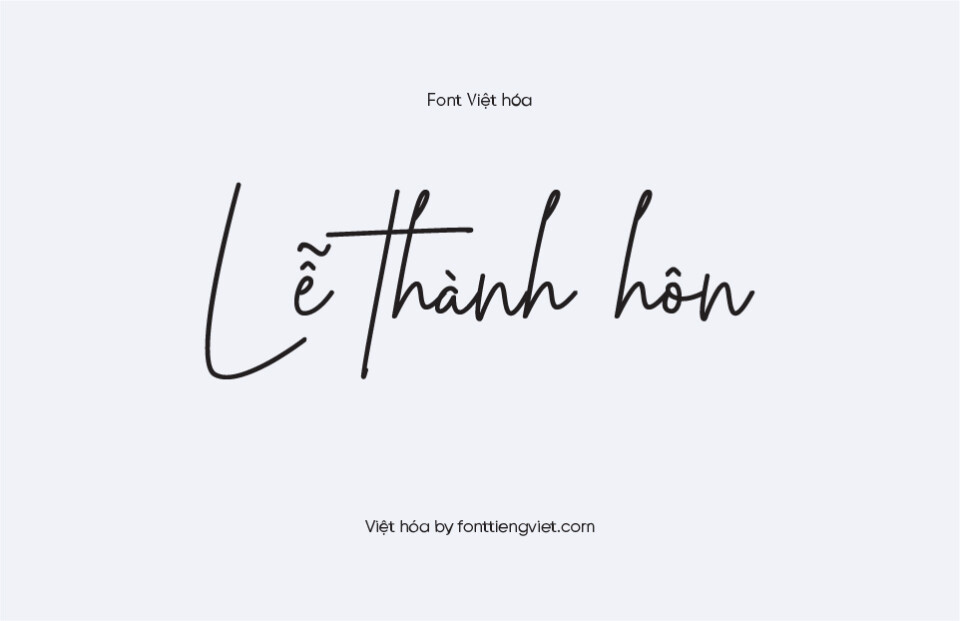
Font Việt hóa 1FTV VIP South Australia
Giới thiệu về Font Việt hóa 1FTV VIP South Australia
Trong thế giới thiết kế đồ họa hiện đại, việc tìm kiếm một bộ font vừa mang tính thẩm mỹ cao vừa hỗ trợ đầy đủ tiếng Việt là điều vô cùng quan trọng. Font Việt hóa 1FTV VIP South Australia nổi lên như một lựa chọn hàng đầu cho các nhà sáng tạo nội dung và học sinh, sinh viên. Đây là một bộ Font Miễn Phí được tinh chỉnh kỹ lưỡng, giúp loại bỏ hoàn toàn các lỗi hiển thị dấu câu thường gặp trong các bộ phông chữ ngoại nhập. Với phong cách thanh lịch và hiện đại, bộ chữ này mang lại cảm giác phóng khoáng nhưng vẫn giữ được sự chuyên nghiệp cần thiết cho mọi sản phẩm thiết kế từ đơn giản đến phức tạp.
Đặc điểm nổi bật của Font Việt hóa 1FTV VIP South Australia
Thiết kế tinh tế và tính ứng dụng cao
Bộ Font Việt hóa 1FTV VIP South Australia sở hữu những đường nét mảnh mai nhưng chắc chắn, tạo nên sự cân đối hoàn hảo trên mặt giấy cũng như màn hình kỹ thuật số. Cấu trúc của các ký tự được thiết kế dựa trên cảm hứng từ vẻ đẹp tự nhiên của vùng Nam Úc, mang đến một hơi thở mới lạ cho cộng đồng thiết kế tại Việt Nam. Độ dày của các nét chữ được tính toán tỉ mỉ để đảm bảo tính dễ đọc ngay cả khi sử dụng ở kích thước nhỏ. Điều này giúp bộ font trở nên cực kỳ linh hoạt, phù hợp cho cả tiêu đề lẫn nội dung văn bản dài mà không gây mỏi mắt cho người xem.
Tối ưu hóa tiếng Việt hoàn chỉnh
Điểm mạnh nhất khiến Font Việt hóa 1FTV VIP South Australia trở nên phổ biến chính là khả năng hiển thị tiếng Việt xuất sắc. Các dấu thanh như huyền, sắc, hỏi, ngã, nặng được đặt ở vị trí chuẩn xác, không bị đè lên ký tự chính hay bị lệch khoảng cách. Đối với các bạn học sinh đang thực hiện báo cáo hay giáo viên thiết kế bài giảng điện tử, việc sử dụng bộ font này sẽ giúp bài trình chiếu trở nên thu hút và chuyên nghiệp hơn rất nhiều. Sự đồng nhất trong thiết kế giữa các ký tự Latinh và các ký tự có dấu tạo nên một tổng thể hài hòa, giúp thông điệp truyền tải một cách trọn vẹn nhất.
Ứng dụng Font Việt hóa 1FTV VIP South Australia trong thực tế
Thiết kế ấn phẩm học đường và văn phòng
Bạn có thể sử dụng Font Việt hóa 1FTV VIP South Australia để làm đẹp cho các tấm thiệp mời, bìa sách, hay các bài thuyết trình PowerPoint. Trong môi trường sư phạm, bộ font này giúp các tài liệu học tập trở nên sinh động, kích thích sự hứng thú của học sinh. Ngoài ra, các văn phòng cũng thường xuyên ứng dụng nó vào thiết kế danh thiếp hoặc thư ngỏ để tạo ấn tượng tốt với đối tác. Nhờ vào sự nhẹ nhàng và thanh thoát, font chữ này dễ dàng kết hợp với nhiều màu sắc và hình ảnh minh họa khác nhau mà không làm lu mờ đi ý tưởng chủ đạo của người thiết kế.
Sử dụng cho nội dung số và mạng xã hội
Với xu hướng sáng tạo nội dung trên Facebook, Instagram hay Canva, việc sở hữu một bộ font lạ mắt là lợi thế lớn. Font Việt hóa 1FTV VIP South Australia giúp các bài đăng của bạn nổi bật hơn giữa đám đông. Khả năng tương thích tốt với các phần mềm đồ họa phổ biến như Adobe Photoshop, Illustrator hay thậm chí là các ứng dụng chỉnh sửa ảnh trên điện thoại giúp người dùng dễ dàng thao tác. Bạn chỉ cần tải về, cài đặt và bắt đầu sáng tạo những tác phẩm nghệ thuật độc đáo mang đậm dấu ấn cá nhân của mình.
Tổng kết về bộ Font Việt hóa 1FTV VIP South Australia
Có thể khẳng định rằng, đây là một trong những bộ phông chữ đáng sở hữu nhất trong bộ sưu tập của bất kỳ ai yêu thích cái đẹp. Sự kết hợp giữa phong cách phương Tây và tâm hồn Việt đã tạo nên một sản phẩm hoàn hảo về mặt thị giác lẫn công năng. Hy vọng rằng với chia sẻ này, bạn sẽ có thêm một công cụ đắc lực để làm mới các dự án của mình. Đừng quên truy cập vào Font Miễn Phí, Font Việt Hóa, Font Việt hóa 1FTV VIP South Australia để trải nghiệm ngay những đường nét tuyệt vời này và chia sẻ nó với bạn bè nếu bạn cảm thấy hữu ích cho công việc hàng ngày của mình.